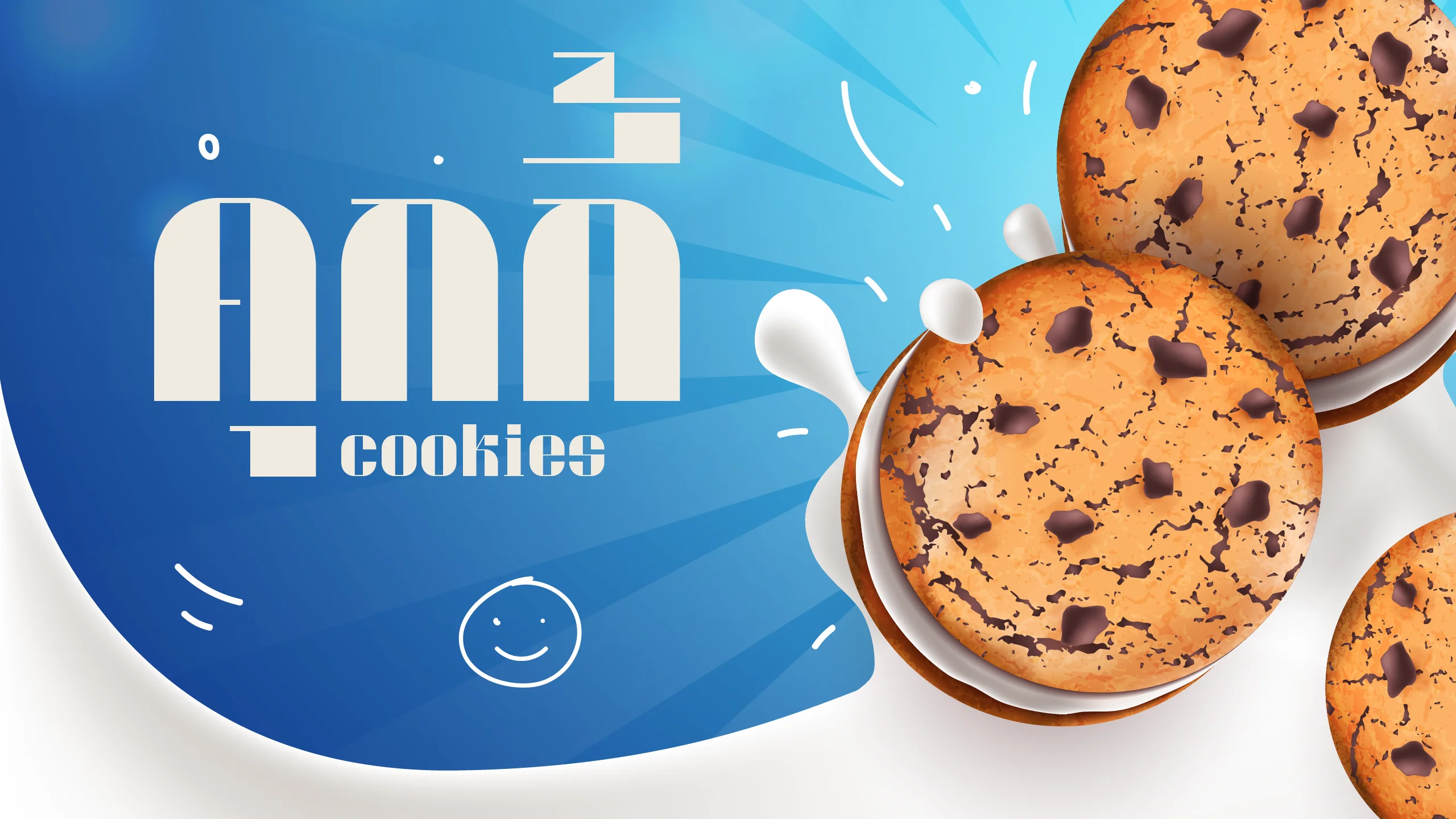
"คุกกี้ | cookies" คือผลลัพธ์จากการเดินทางของตัวอักษรที่เริ่มต้นขึ้นท่ามกลางบรรยากาศหอมกรุ่นของร้านกาแฟและเบเกอรี่ โดยเราหยิบยกรูปทรงอันเป็นเอกลักษณ์ของเมล็ดกาแฟมาถ่ายทอดเป็นเส้นสายที่มีจังหวะความหนาบางชัดเจน ให้ความรู้สึกที่อบอุ่น อ่อนโยน แต่ยังคงความโมเดิร์นที่โดดเด่นสะดุดตา เหมาะอย่างยิ่งสำหรับการสร้างแบรนด์ที่ต้องการความเป็นมิตรและเข้าถึงง่าย เพื่อให้ตอบโจทย์การใช้งานที่สมบูรณ์แบบ เราจึงพัฒนาฟอนต์ชุดนี้ออกมาถึง 2 รูปแบบที่มีความกว้างของตัวอักษรแตกต่างกัน ช่วยให้นักออกแบบสามารถเลือกใช้ให้เข้ากับพื้นที่จัดวางได้อย่างอิสระ ไม่ว่าจะเป็นการพาดหัวตัวใหญ่บนป้ายหน้าร้าน หรือการวางรายละเอียดในเมนู cookies จึงไม่ใช่แค่ฟอนต์ที่มีที่มาน่าประทับใจ แต่ยังเป็นเครื่องมือที่ช่วยเติมเต็มงานดีไซน์ของคุณให้มีชีวิตชีวาและลงตัวในทุกรายละเอียด